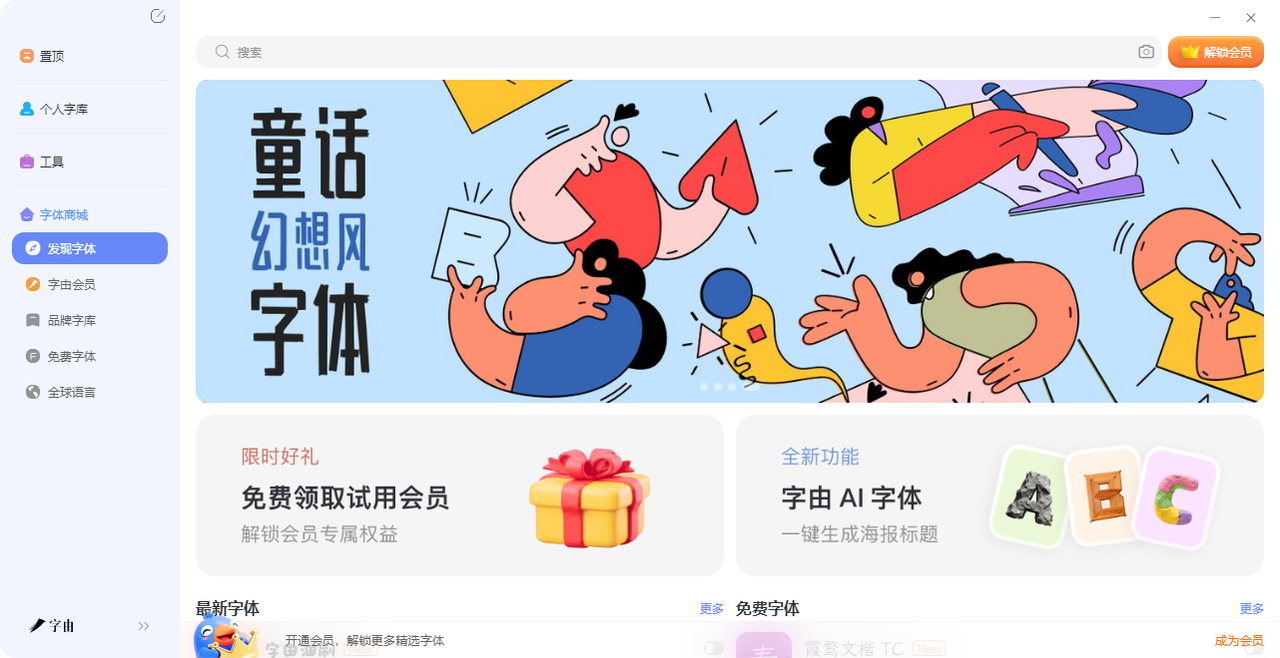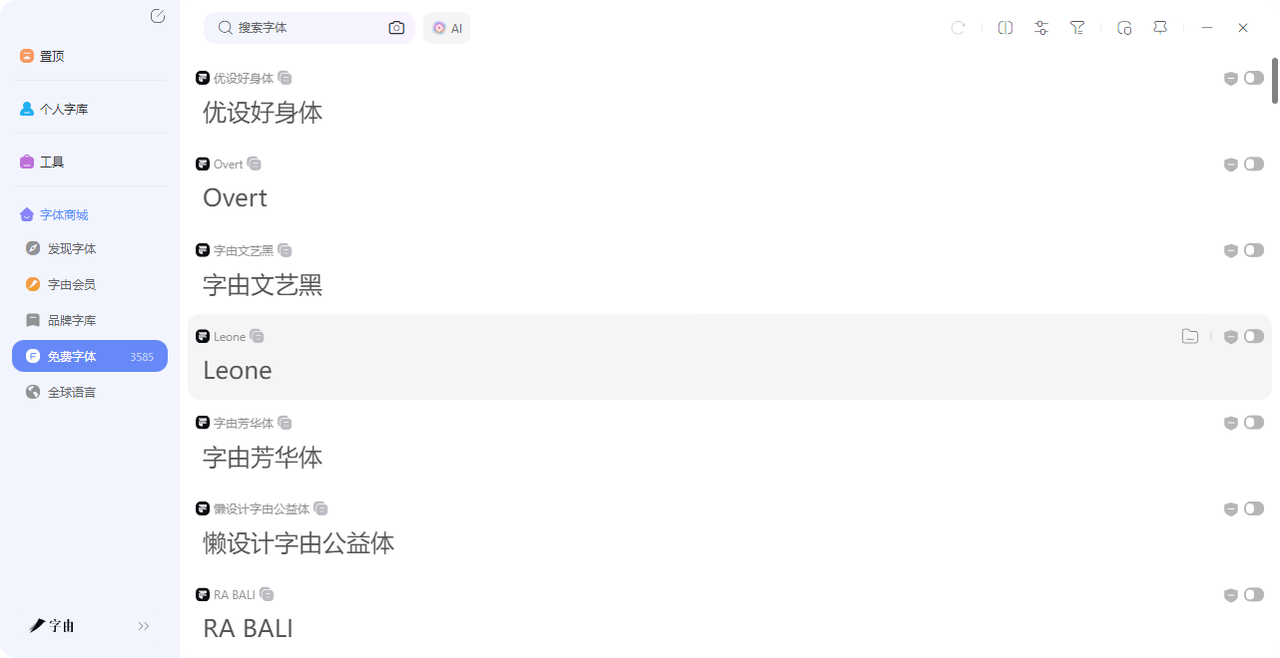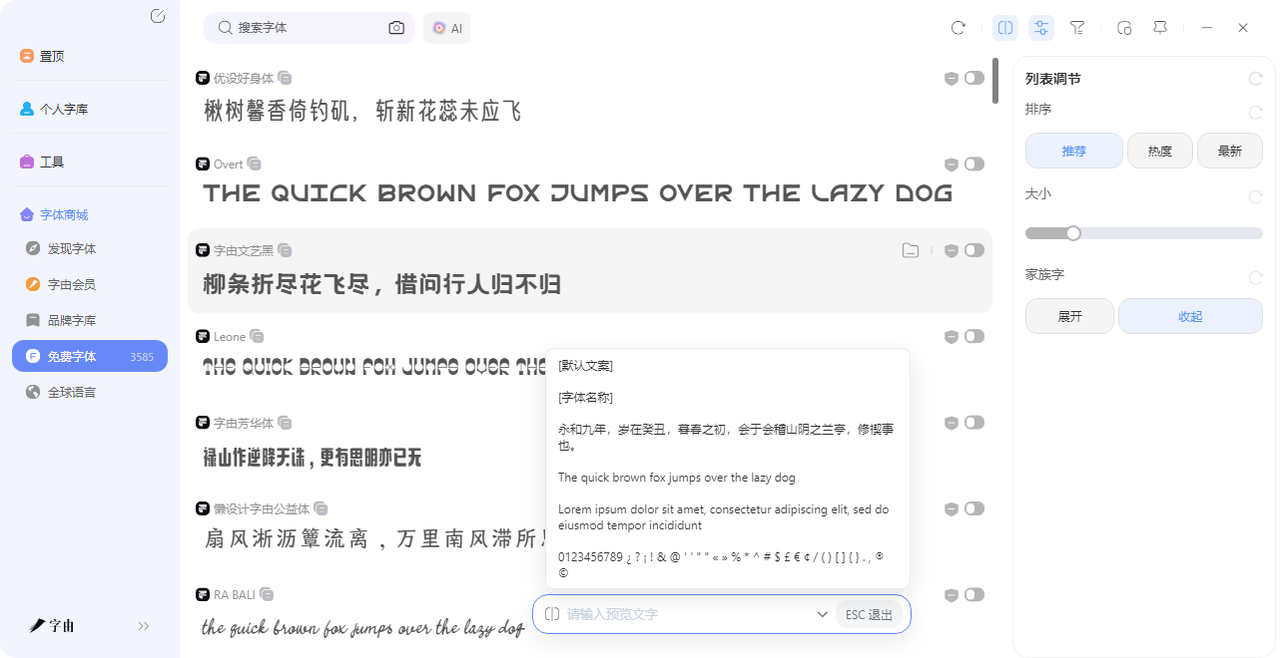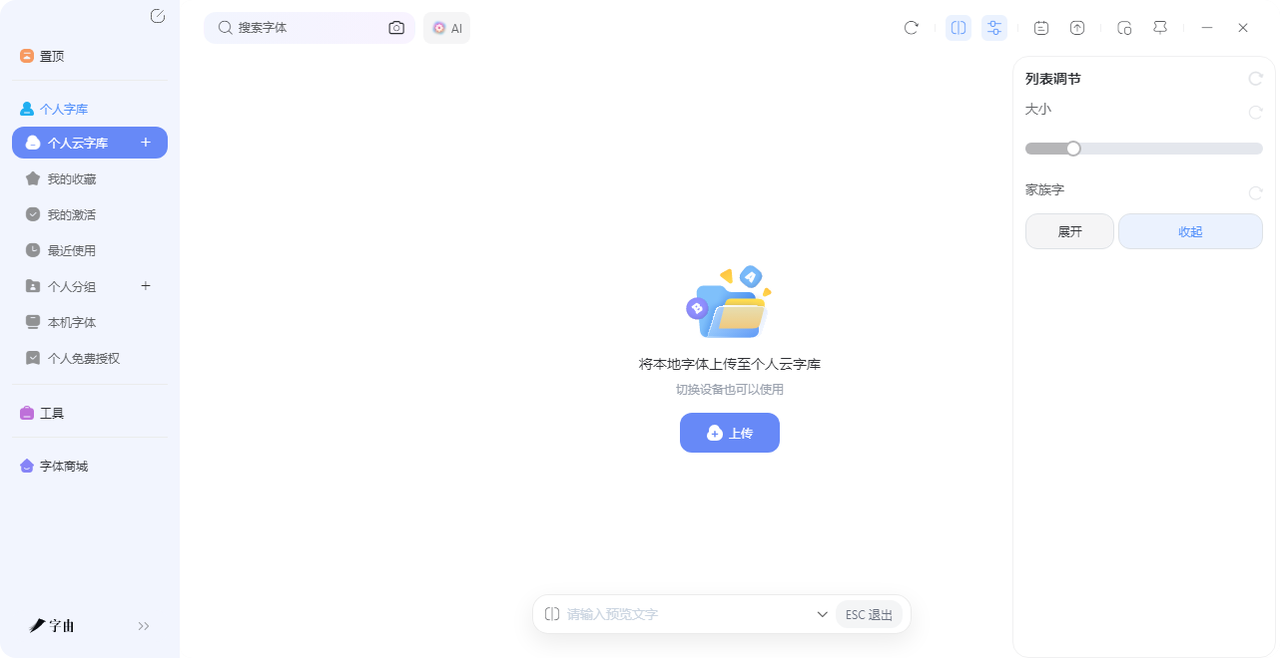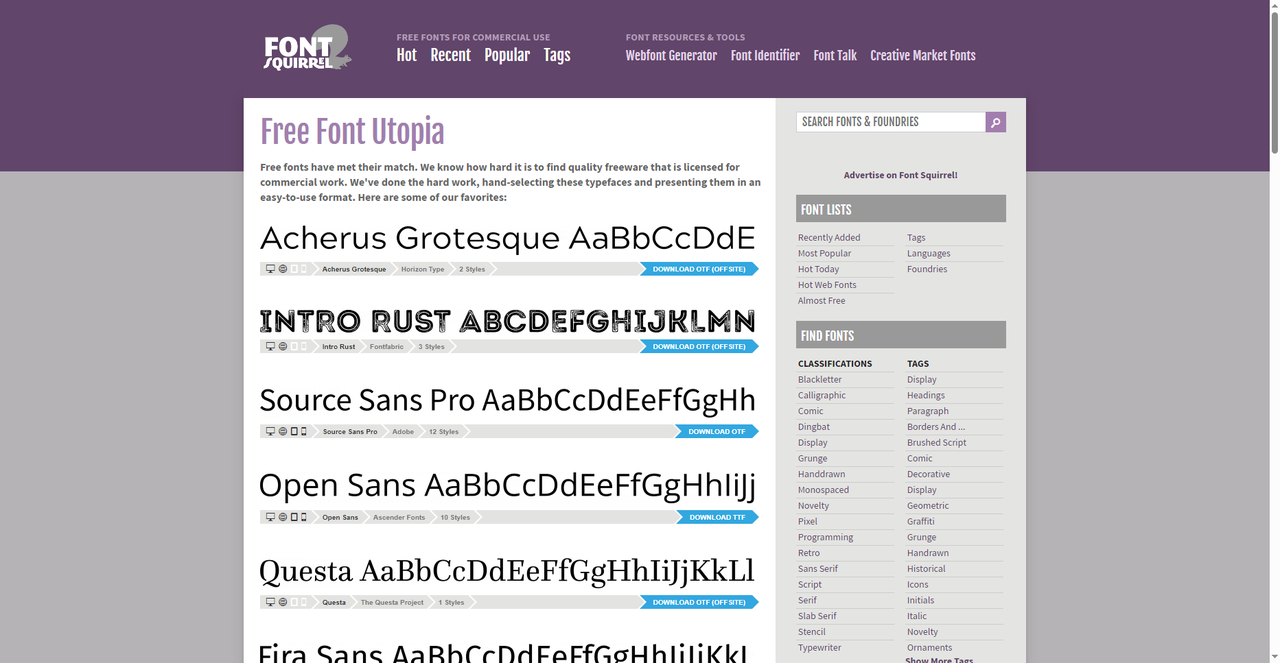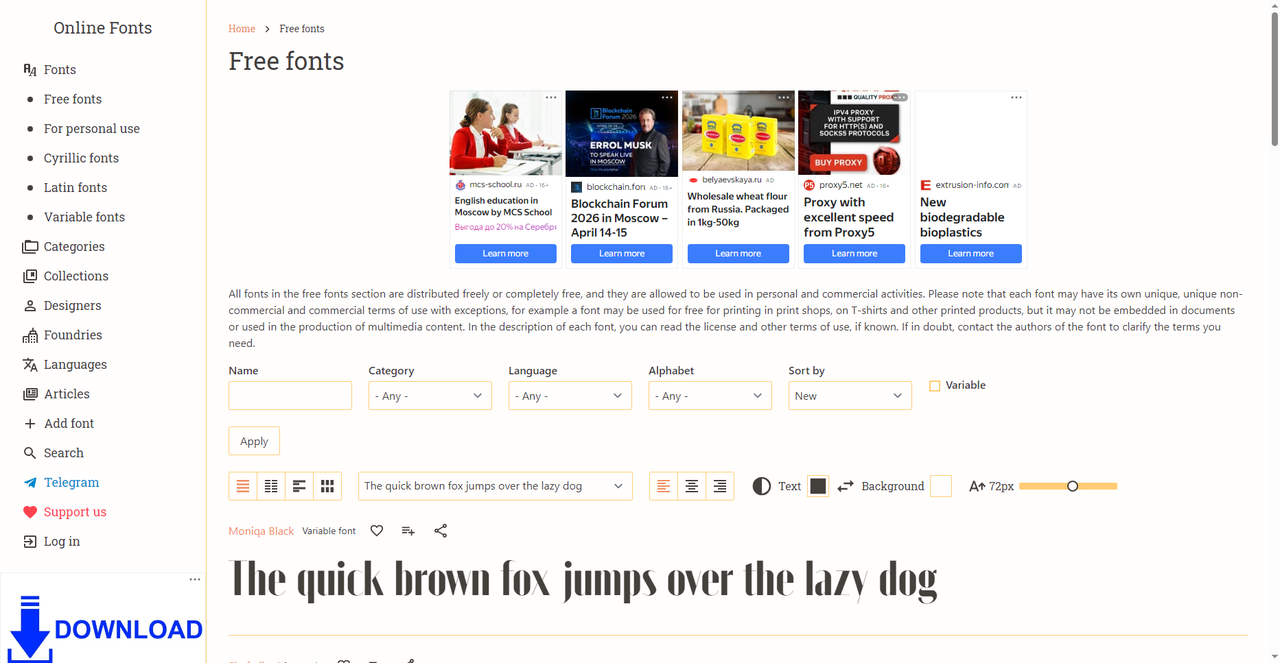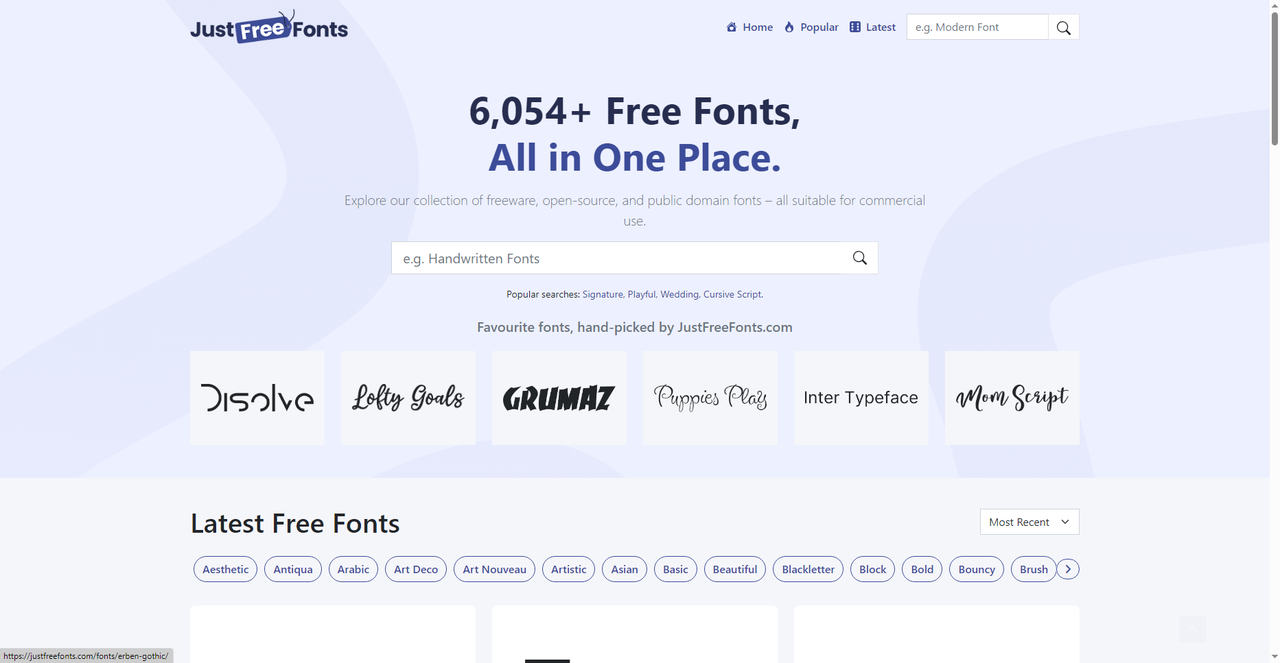
别再为字体版权提心吊胆了!无版权免费字体了解一下
前一阵子做海报的时候特意挑选了一些比较有设计感的字体,朋友们看了都觉得不错,但是其中一个人问了我一个问题说“这个字体有版权吗?商用的话会不会有侵权的危险?”这我才反应过来我用的时候没有查版权,还好后面找到是免费商用的。但是自那以后我每次找字体都必须确定是不是可以免费商用的。但是这样又太费时间,所以后面我直接找了很多无版权字体网站,这样就可以一键解决单词的版权问题。今天就把我收藏的4 个无版权免费字体网站分享出来,授权清晰。需要的直接收藏,以后做设计再也不用为版权发愁。
字由是我用过最省心的无版权免费字体工具。它把“找字体”这件事,从“到处搜、下载、安装、重启”压缩成了“点一下筛选、看预览、一键应用”。
• 打开字由,左侧筛选栏直接点“免费商用”,系统立刻从一万多款字体里筛出3585 款无版权免费字体。这3585 款全部标注了授权类型,用着放心,不用再猜“这个能不能商用”。想找国风字体,点“中国风”;想要手写感,点“手写体”;想做电商标题,点“黑体”。三秒定位,不用一页页翻。
• 每款字体右下角都有一个使用次数。“字由文艺黑”1436万次,“优设好身体”503万次,“沐瑶软笔手写”445万次——这些数字意味着大量设计师替你验证过了,踩坑的概率很低。我一般优先看热度高的,省时省力。
• 点进任何一款字体,都有一个预览框。把你想用的文案输进去,比如“春日来信”“开业大吉”,字体会自动用你的文案展示效果。不用下载,不用安装,看一眼就知道合不合适。确认之后,在PS里选中文字图层,回到字由点一下字体,文字就换好了。不用重启软件,不用等。
接下来我也会推荐几款常用的无版权免费字体
• 优设好身体:字形方正饱满,做画册内页、公众号配文很稳,不会抢画面的风头。
• 字由文艺黑:既有黑体的稳重,又带着一点手写感。做海报主标题、品牌Logo,或者需要“正式但不死板”的感觉时,用它很对味。
• 沐瑶软笔手写:圆润治愈的软笔风格,做亲子类海报、手账内容、温暖治愈的社交媒体配图,用它很出片。
• 点字浅夏体:清新手写,做旅行vlog封面、生活记录类标题,很加分。
而且,最主要的是,你可以把你用过的或者是喜欢的字体放到字由的个人云字库里,把常用的无版权免费字体上传到云端,换电脑登录账号,直接就能用。不用U盘拷来拷去,也不用担心电脑坏了字体丢失。
2、Font Squirrel
Font Squirrel 是一个老牌无版权免费字体网站,它的口号是“Free Font Utopia”。网站首页就写着:“我们深知找到授权用于商业工作的免费字体有多难,因此手动挑选了这些字体。”每一款都是人工审核,确保真正免费可商用。我在这个网站里常用的字体有:
• Acherus Grotesque:现代无衬线体,2种字重
• Intro Rust:粗犷有力,3种字重
• Source Sans Pro:Adobe出品,12种字重,经典开源字体
• Open Sans:Ascender Fonts出品,10种字重
• Questa:优雅衬线体,1种字重
Font Squirrel 的字体质量普遍很高,而且下载前有详细的预览和字符集展示。它还提供网页字体生成器,方便网页设计师使用。如果你不想在海量字体里大海捞针,这里的人工精选会让你很省心。“网页字体生成器”这个功能很实用,做网站的时候上传字体文件,自动生成@font-face 代码,直接复制到CSS里就能用,不用自己手写。“字符集预览”这块很实用,能提前看到这款字体包含哪些字母和符号。做多语言设计的时候,直接看预览就知道支不支持,不用下载之后才发现缺字符。
3、Online Fonts
Online Fonts 是一个免费字体下载网站,它的“Free fonts”板块收录了大量无版权免费字体。首页有一段说明很关键:“All fonts in the free fonts section are distributed freely or completely free, and they are allowed to be used in personal and commercial activities.”——所有免费字体都允许用于个人和商业活动。
但网站也提醒了:每款字体可能有不同的使用条款,比如有的可以用于印刷,但不能嵌入文档或用于多媒体内容。所以在下载前,最好看一眼字体描述里的授权说明。网站支持按类别、语言、字母排序筛选,还提供了实时预览功能,输入文字就能看效果。“实时预览”这个功能很顺手,输入文字就能看到效果,不用下载就知道合不合适。而且它家的语言筛选很细,做多语言项目的时候可以直接选。“按字母排序”这个功能也方便,知道字体名字的话直接跳转,不用一页页翻。而且它家还标注了每种字体的使用条款,比如“可印刷但不可嵌入”,很清晰。
4、JustFreeFonts
JustFreeFonts 的首页写着6000多款免费字体,全部适合商用。这个定位非常清晰,就是帮你找无版权免费字体。网站首页有热门搜索推荐,比如“Signature”“Playful”“Wedding”“Cursive Script”,方便你快速定位。还展示了精选字体。
每款字体都标注了设计师和风格(Handwritten、Display、Sans Serif),还有“Latest Free Fonts”板块,展示最新上架的免费字体。这个网站的优势是更新快、精选度高,适合经常逛一逛。“Latest Free Fonts”板块我经常翻,每周都有新字体上架。有时候能淘到刚出的热门款,比别人早用上,做出来的设计也不容易撞款。
这么看来先找到无版权可免费商用的字体并不是一件难事,重点的是要找到合适的网站,找到真正合适的网站才能做到没有版权相关的忧虑,也剩下了精力和时间,每个网站都在帮你解决同一个问题:让设计不再有版权焦虑。但是我还是最喜欢用字由,它不只是给你字体,更帮你把字体管起来,个人云字库、品牌专区,用起来确实省心。如果你也经常为字体版权发愁,不妨从字由开始试试,让设计真正自由。